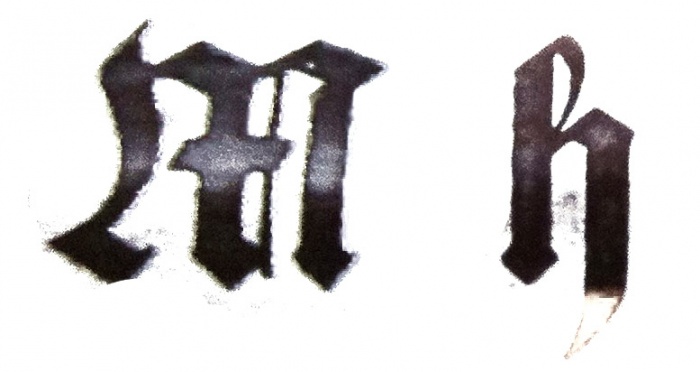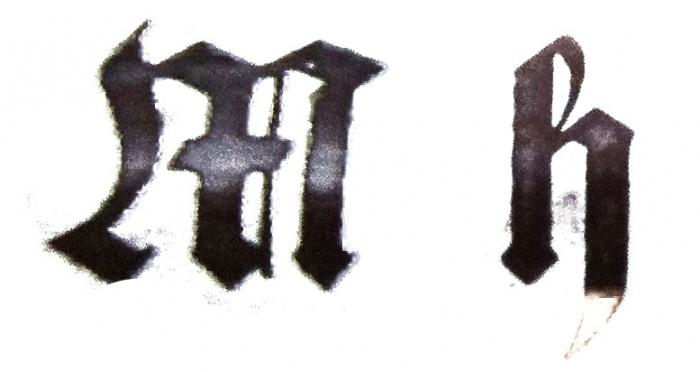
Suche spezielle Fraktur
nach einiger Recherche bin ich ziemlich am Ende.
Wir arbeiten aktuell alte Dokumente auf und haben fast alle Fonts im Portfolio bzw. einkaufen können nach Recherche.
Zu dieser Fraktur haben wir bisher aber nichts weiter gefunden, ausser diesen Font:
https://www.myfonts.com/fonts/aerotype/gothicus/
Problem: wackelige Typo, nicht clean wie eigentlich gebraucht und keine 100% Übereinstimmung.
Ein Auszug der Fraktur habe ich euch angehangen.